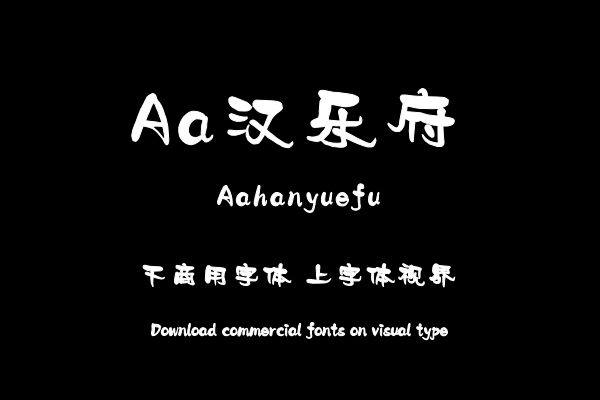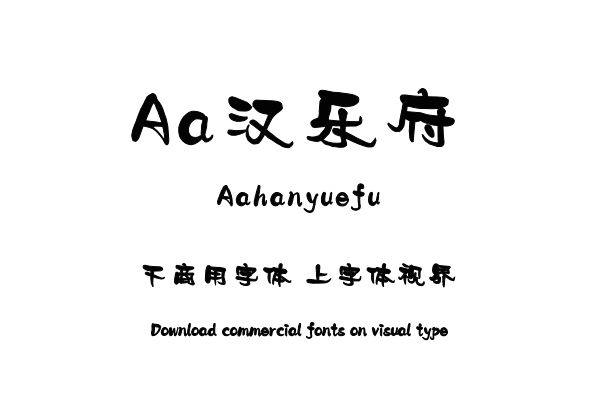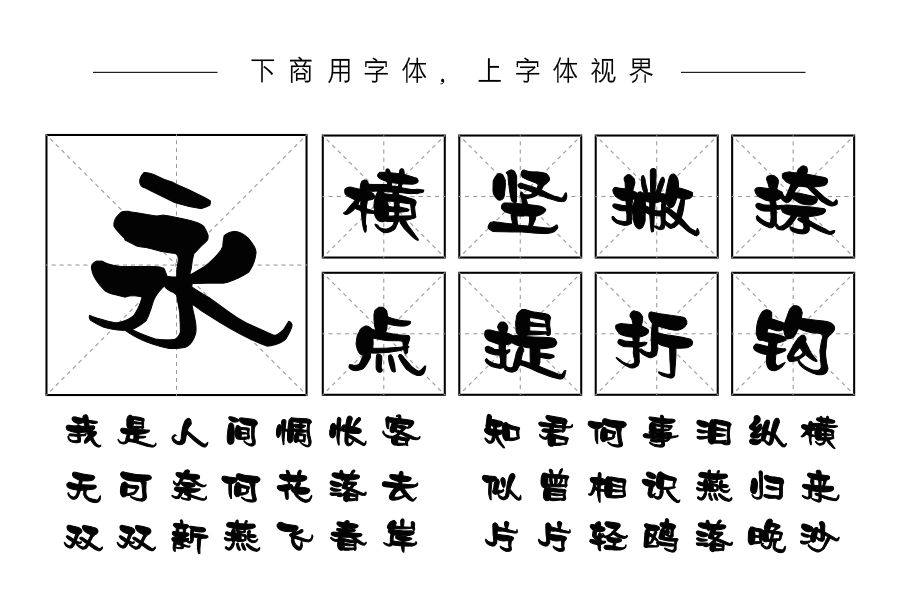
笔画歪曲的同时又不失流畅,笔画尾部的勾勾装饰,让整个字变得有趣诙谐,粗细对比强烈,过渡自然,适合各类广告和产品包装设计应用。购买须知:“下载服务费”与“字体VIP”所获得字体 仅用于个人非商用, 商用请联系付费授权。本字体为电脑用字,手机没有root权限不支持直接手机换字(手机如何root,请自行百度搜索教程)。购买前请先 了解清楚后再付款 ,字体为虚拟产品无法回收 一旦购买不支持退款。